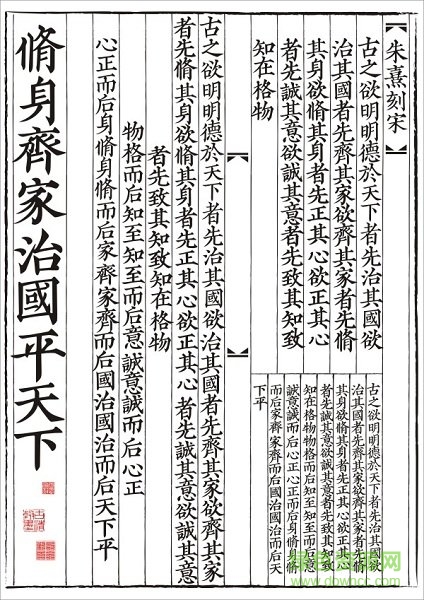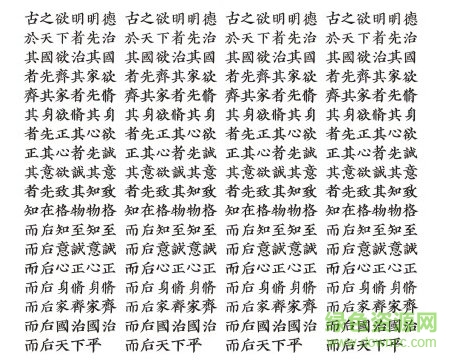
朱熹刻宋是彦辰设计推出的一款刻宋字体,还原宋刻本古籍字体特色,给人镌刻印刷的视觉体验,文字质朴而大气,结构端正而松疏有致,十分简洁好看,绿色资源网今日推荐!
“朱熹刻宋”字体设计以宋朝淳佑朱熹注解的《大学章句》刻本字形为蓝本,将刻本字体按照现代平面设计需求进行了修复、调整和优化,设计师对大部分字形进行了框架保留,将刀工失真之处进行了机械性修复,使其成为符合现代版式审美需求的新字形,同时尽量呈现宋刻本的原汁原味,整体感观上更加古朴渊雅。
在古籍善本市场上,宋刻本无疑是皇冠上的钻石。自明中后期以来,宋刻本一直受到学者、藏书家的特别重视。早在明朝,宋刻本已有“寸纸寸金”之说。
宋刻本之美主要在于字体、版式。事实上,中国自唐代就已有雕版印书,五代有以国子监为代表的官刻本,但雕版印刷却长期未被普遍采用,而仍以手抄的写本为主,原因之一就是,写本洋溢着书法艺术气息,其美感使人油然产生阅读的愉悦。而初始的雕版印刷品,常常会有滞涩呆板、索然无味的感觉。
中国的书法艺术,历经汉代、南北朝及唐代三个高潮之后,到了宋代已极为繁荣。宋代为推广雕版印刷,也从书法的角度考虑兼顾实用性和观赏性。从目前留存的北宋版和南宋刻本的名品看,几乎都出自擅长书法的人之手,且书体风格不一,欧、虞、颜、柳、褚等争奇斗妍,富于变化,加上雕印讲究(纸墨精良,刻工也懂书法),艺术之美跃然纸上。